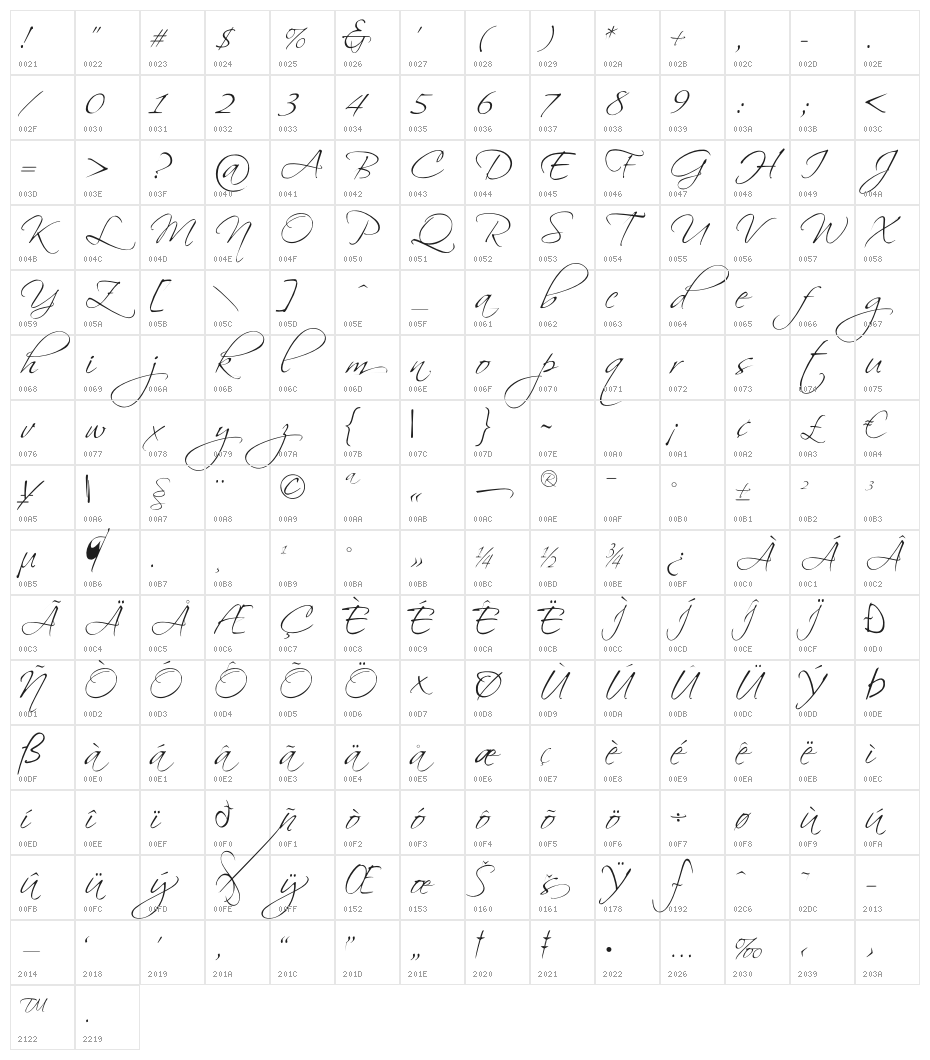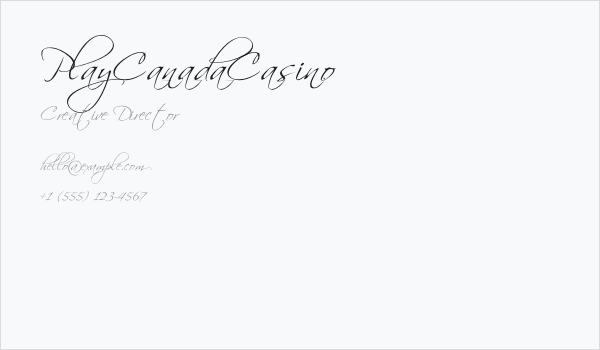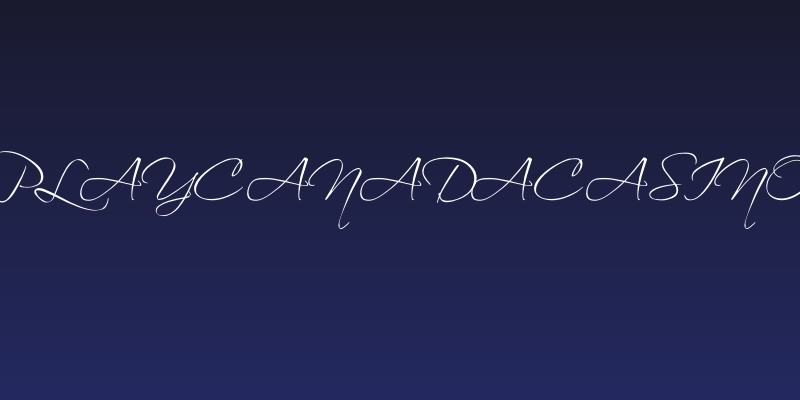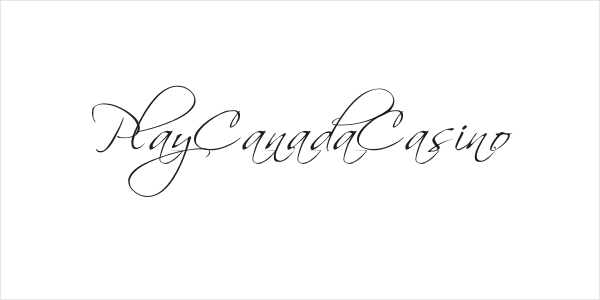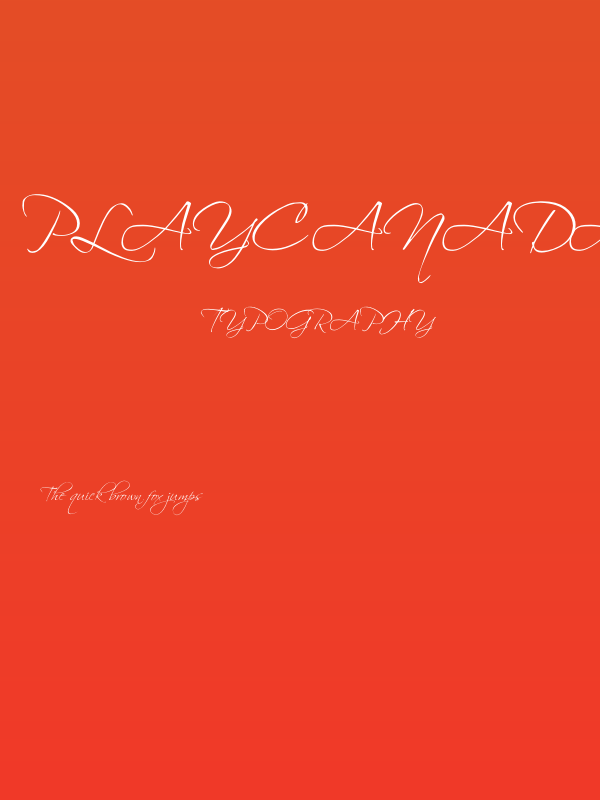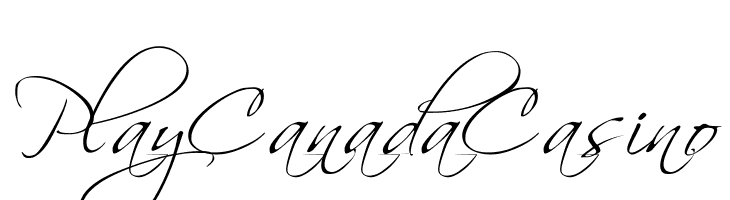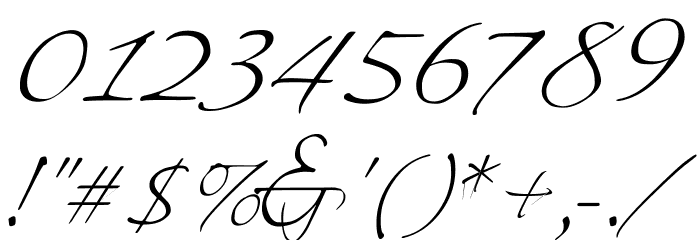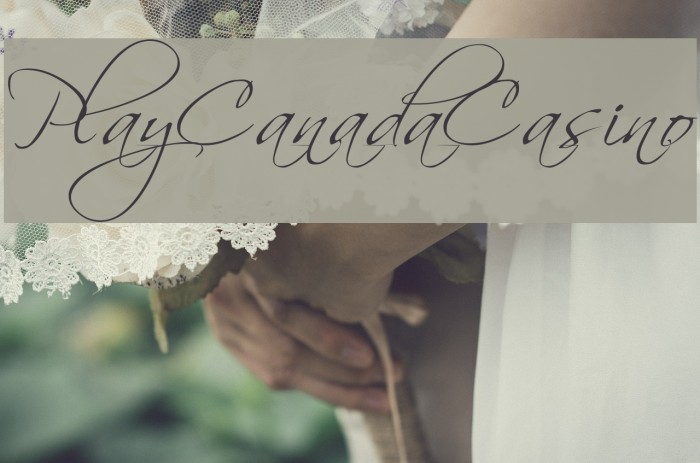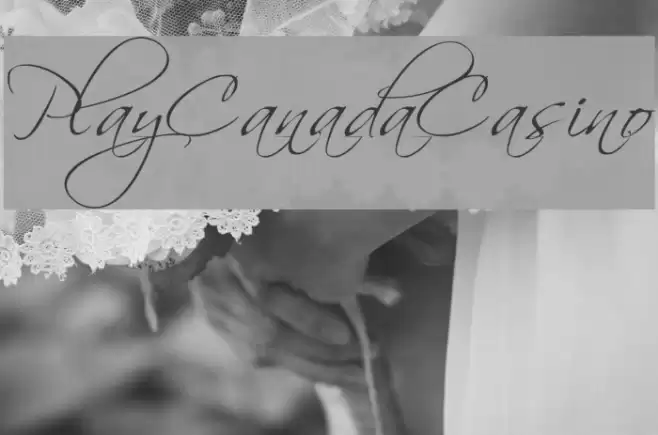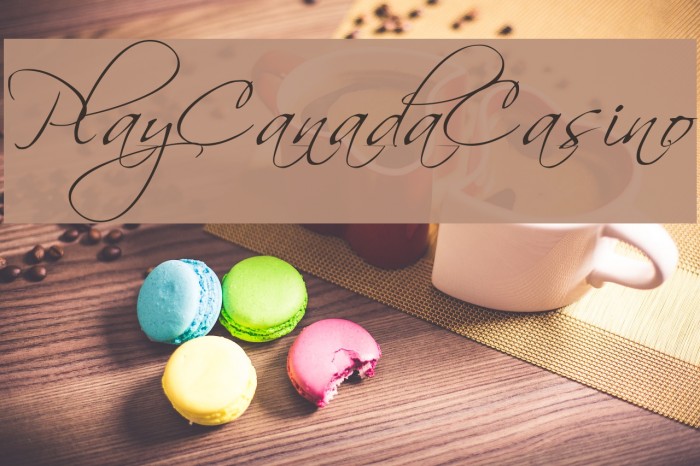
PlayCanadaCasino Font
✎ Script
| Caso de uso | Logos, Invitations, Artistic projects |
| Proyectos propuestos | Ideal for wedding invitations, luxury branding, high-end product packaging, and artistic projects requiring a touch of elegance. |